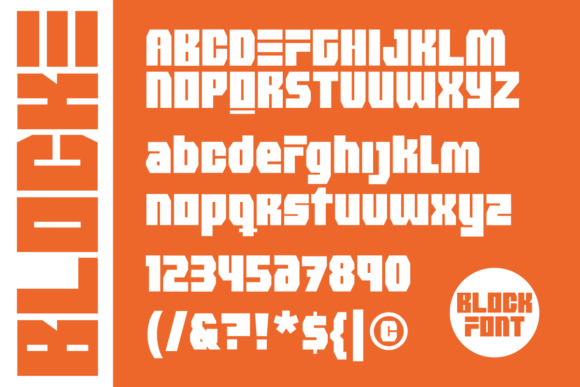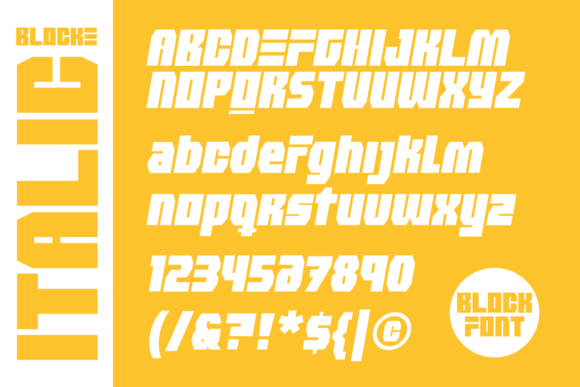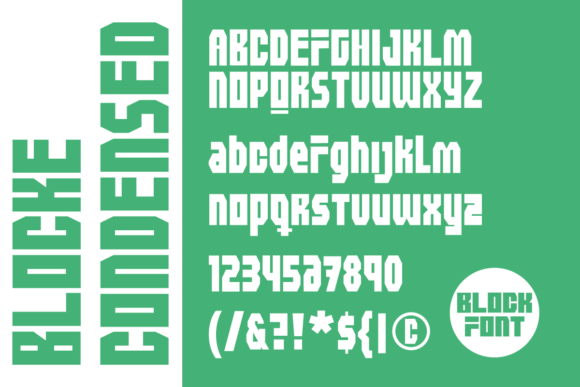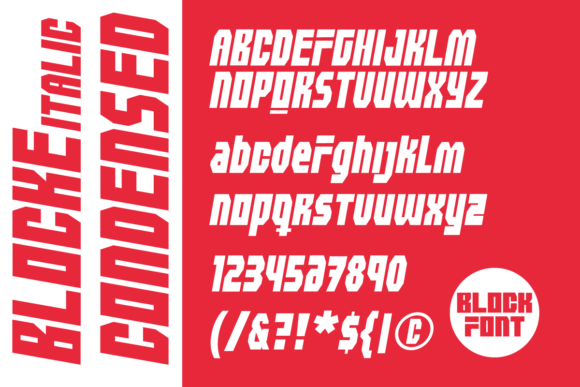
Introducción a BLOCKE: La Fuente Moderna de Tipo Bloque
En el mundo del diseño gráfico, la elección de la fuente adecuada puede hacer toda la diferencia en la creación de proyectos visualmente impactantes. Una de las fuentes más destacadas en la actualidad es BLOCKE, una fuente moderna de tipo bloque que se está convirtiendo en la opción favorita de diseñadores y creativos. En este artículo, exploraremos las características y ventajas de BLOCKE, y por qué es perfecta para proyectos de grandes dimensiones.
Características de BLOCKE
BLOCKE es una fuente de tipo bloque que se caracteriza por su diseño limpio y minimalista. Su contador es muy estrecho, lo que la hace ideal para proyectos de grandes dimensiones como vallas, pósters artísticos, señalización, packaging, títulos y logotipos. Debido a su diseño, se recomienda no utilizarla en tamaños pequeños, ya que la definición de cada carácter se perderá. Sin embargo, cuando se utiliza en tamaños grandes, BLOCKE ofrece una presencia imponente y una legibilidad excepcional.
Ventajas de BLOCKE
BLOCKE ofrece varias ventajas que la hacen destacar en el mundo del diseño gráfico. Algunas de sus ventajas incluyen:
- Diseño impactante: BLOCKE es perfecta para crear diseños impresionantes y visualmente impactantes. Su diseño de tipo bloque la hace ideal para llamar la atención y transmitir mensajes de manera efectiva.
- Versatilidad: BLOCKE se puede utilizar en una variedad de proyectos, desde vallas y pósters hasta packaging y logotipos. Su versatilidad la hace una excelente opción para diseñadores y creativos.
- Limpieza y minimalismo: BLOCKE cuenta con un diseño limpio y minimalista que la hace ideal para proyectos que requieren una estética moderna y sofisticada.
Uso de BLOCKE en Proyectos de Diseño
BLOCKE es una fuente muy versátil que se puede utilizar en una variedad de proyectos de diseño. Algunos ejemplos de proyectos que se pueden beneficiar de BLOCKE incluyen:
- Vallas y señalización: BLOCKE es perfecta para vallas y señalización debido a su tamaño grande y su diseño impactante.
- Pósters artísticos: BLOCKE se puede utilizar para crear pósters artísticos que requieren una fuente grande y llamativa.
- Packaging: BLOCKE se puede utilizar para packaging de productos que requieren una fuente moderna y sofisticada.
- Logotipos y títulos: BLOCKE es ideal para logotipos y títulos que requieren una fuente grande y impactante.
Consejos para Utilizar BLOCKE
Para aprovechar al máximo BLOCKE, aquí hay algunos consejos:
- Utilízala en tamaños grandes: BLOCKE se ve mejor en tamaños grandes, así que asegúrate de utilizarla en proyectos que requieran una fuente grande y impactante.
- Combina con otras fuentes: BLOCKE se puede combinar con otras fuentes para crear un diseño más interesante y variado.
- Experimenta con colores y texturas: BLOCKE se puede utilizar con diferentes colores y texturas para crear un diseño más dinámico y visualmente atractivo.
Conclusión
BLOCKE es una fuente moderna de tipo bloque que se está convirtiendo en la opción favorita de diseñadores y creativos. Su diseño limpio y minimalista, su versatilidad y su capacidad para crear diseños impactantes la hacen ideal para proyectos de grandes dimensiones. Al seguir los consejos y recomendaciones de este artículo, podrás aprovechar al máximo BLOCKE y crear diseños visualmente atractivos y efectivos.